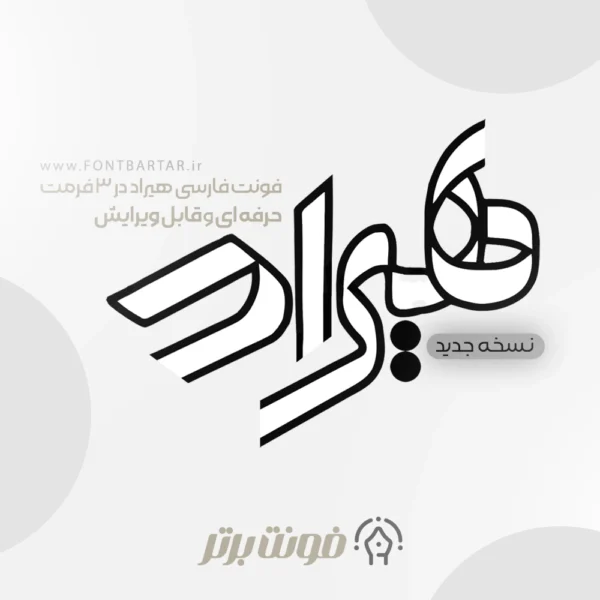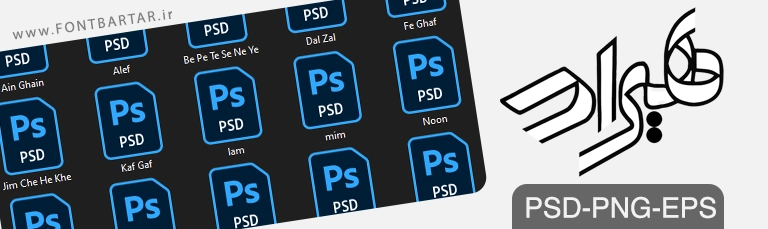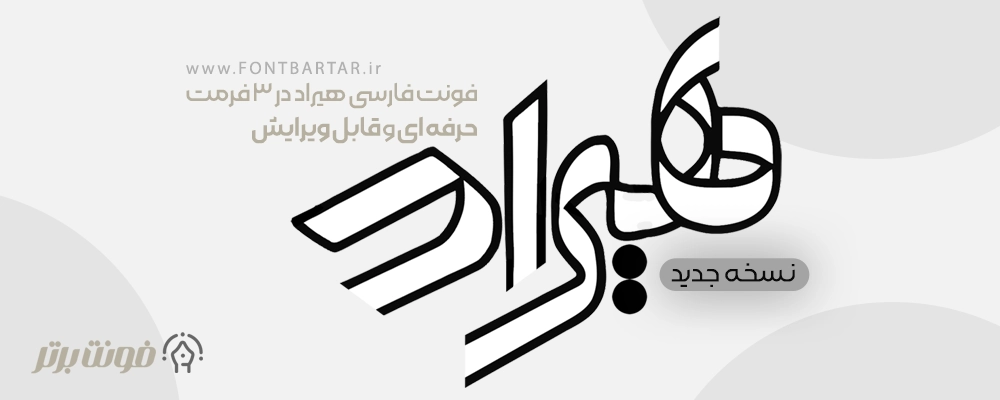
فونت لایه باز هیراد
فونت فارسی هیراد
Hirad Font
فونت فارسی هیراد
دانلود فونت لایه باز هیراد
دانلود فونت فارسی هیراد (Hirad Font) – فونتی حرفه‌ای و لایه باز برای طراحی
فونت هیراد یکی از خاص‌ترین و حرفه‌ای‌ترین فونت‌های فارسی طراحی‌شده توسط مجموعه فونت برتر (Fontbartar.ir) است، این فونت با طراحی خاص و زاویه‌دار خود، حس مدرن، قدرت و خلاقیت را به طراحی‌های فارسی شما منتقل می‌کند.
فونت هیراد یکی دیگر از فونت های طراحی لوگوتایپ و تایپوگرافی می باشد، فونت فارسی هیراد با طراحی حرفه ای و انعطاف پذیر می باشد و این امکان را فراهم می آورد که به راحتی بتوانید حروف را در کنار هم قرار دهید، با خرید فونت فارسی هیراد می توانید بدون هیچگونه دانشی لوگو تایپ طراحی کرده و تایپوگرافی های زیبایی انجام دهید و از آن کسب درآمد کنید.
فونت هیراد بر خلاف سایر فونت ها به صورت لایه باز بوده (psd) و امکان تایپ مستقیم در نرم افزار ها را ندارد همچنین شامل تمامی حروف از الف تا ی می شود این فونت به چینش های مختلف می تواند در کمترین زمان این امکان را به طراح بدهد که یک لوگو تایپ حرفه ای برای کسب و کار های مختلف طراحی کند ویژگی های این فونت حرفه ای را باهم مرور کنیم.
مزایای استفاده از فونت فارسی هیراد :
• تمامی حروف به صورت لایه باز
• ویرایش آسان حروف
• طراحی لوگوتایپ
• طراحی لوگو به صورت آسان و بدون هیچگونه آموزش
• سریع و بدون وقت گیری
• شامل تمامی حروف از الف تا ی در تمامی حالت ها
بهترین فونت لایه باز هیراد
🎯 کاربرد فونت هیراد در طراحی
فونت هیراد به‌خاطر ساختار خاص و زیبای خود در طراحی‌های متنوعی استفاده می‌شود از جمله:
1. طراحی لوگوتایپ‌های فارسی خاص و مدرن
2. تایپوگرافی‌های تبلیغاتی و هنری
3. طراحی جلد مجلات و پوسترهای فرهنگی
4. ساخت بنر و پست‌های شبکه‌های اجتماعی
طراحی سریع لوگو
1. فونت هیراد برای چه نوع طراحی مناسب است؟
برای طراحی لوگو، تایپوگرافی، پوستر، جلد کتاب، تبلیغات و طراحی‌های مدرن فارسی عالی است.
2. آیا فونت هیراد از تمام حروف فارسی پشتیبانی می‌کند؟
بله، این فونت از تمامی حروف فارسی پشتیبانی کامل دارد.